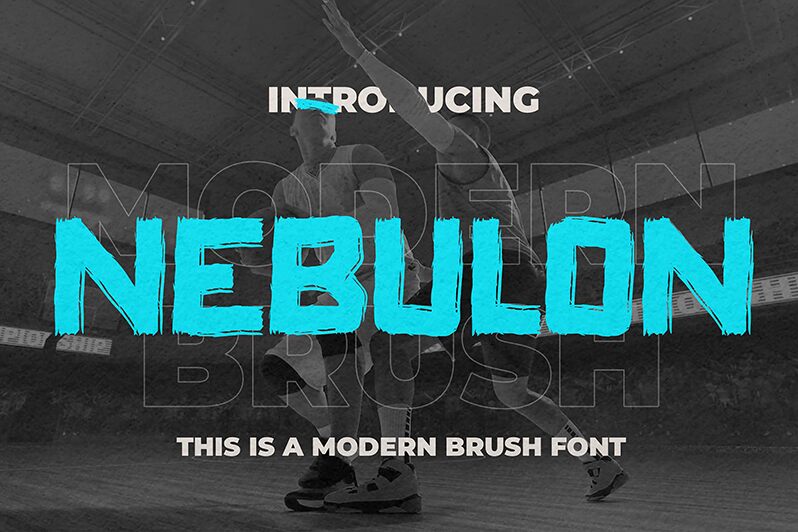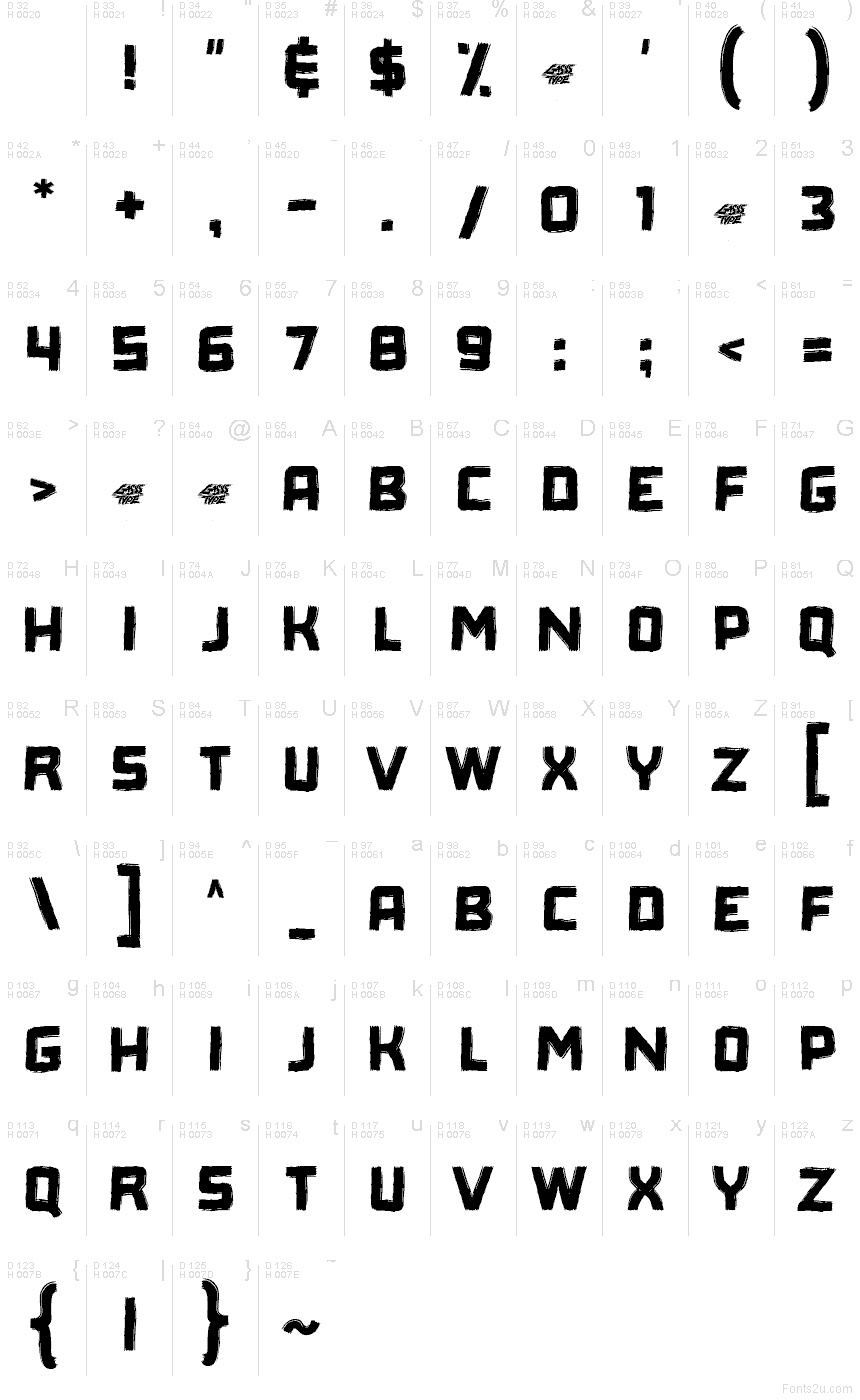
Nebulon di Gassstype Studio è un font gratuito in maiuscolo in stile «dry-brush», con un carattere ruvido e sci-fi. Le lettere sembrano dipinte di getto con un pennello largo, lasciando bordi irregolari, texture striata e forme piene che conferiscono al logo un aspetto aggressivo, tutt'altro che levigato.
Questo rende questo font gratuito una scelta naturale per titoli di poster, grafica di videogiochi, copertine di album, branding streetwear e titoli dove parole brevi necessitano di un impatto graffiato e fatto a mano. Funziona benissimo anche per monogrammi e grandi iniziali, poiché le maiuscole hanno abbastanza spessore da sostenere la texture ruvida senza perdere la forma.